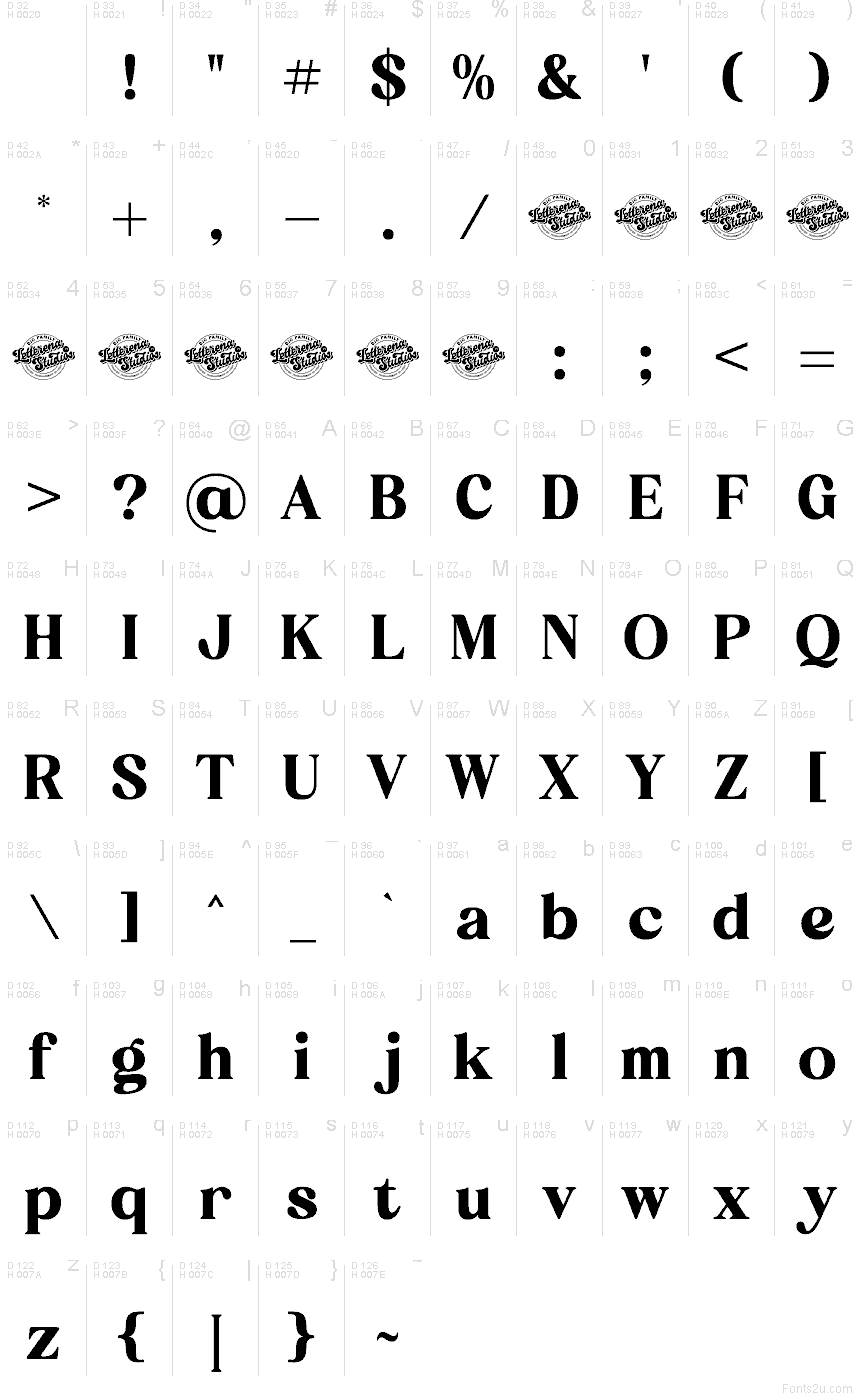
Histore Magical, da Letterena Studios, é uma fonte serifada gratuita de alto contraste. Serifas ultrafinas encontram hastes verticais largas, e suas letras esguias alternam entre maiúsculas imponentes e minúsculas de contornos suavemente arredondados.
As embalagens de moda representam seu melhor cenário de uso, principalmente em rótulos de perfumes e no branding de cosméticos, que se beneficiam de seu traço nítido e refinado. Ela também combina com cabeçalhos de revistas e cartazes de eventos com temas formais ou dramáticos. O estilo agradará principalmente aos designers das áreas de beleza, moda e design editorial.